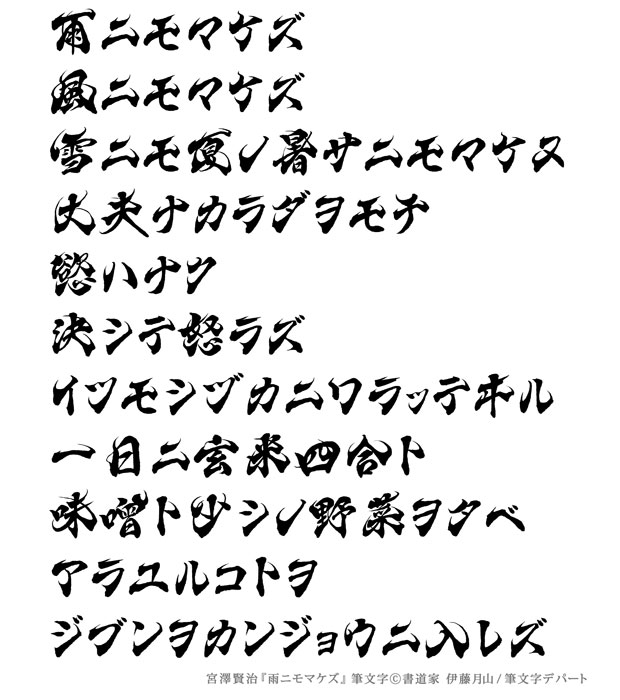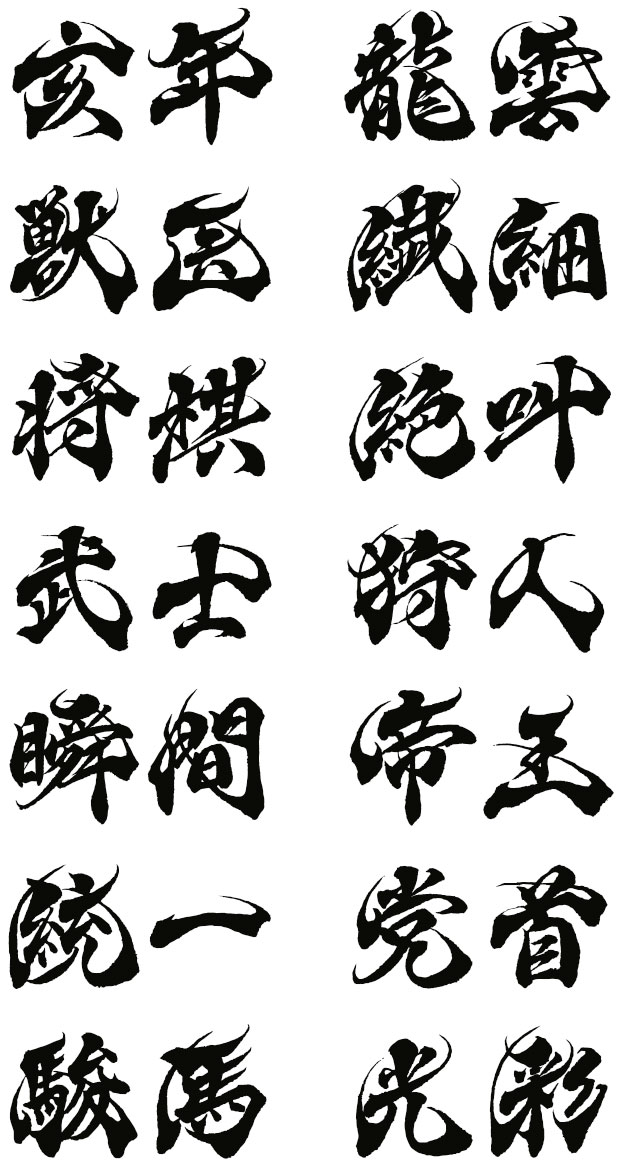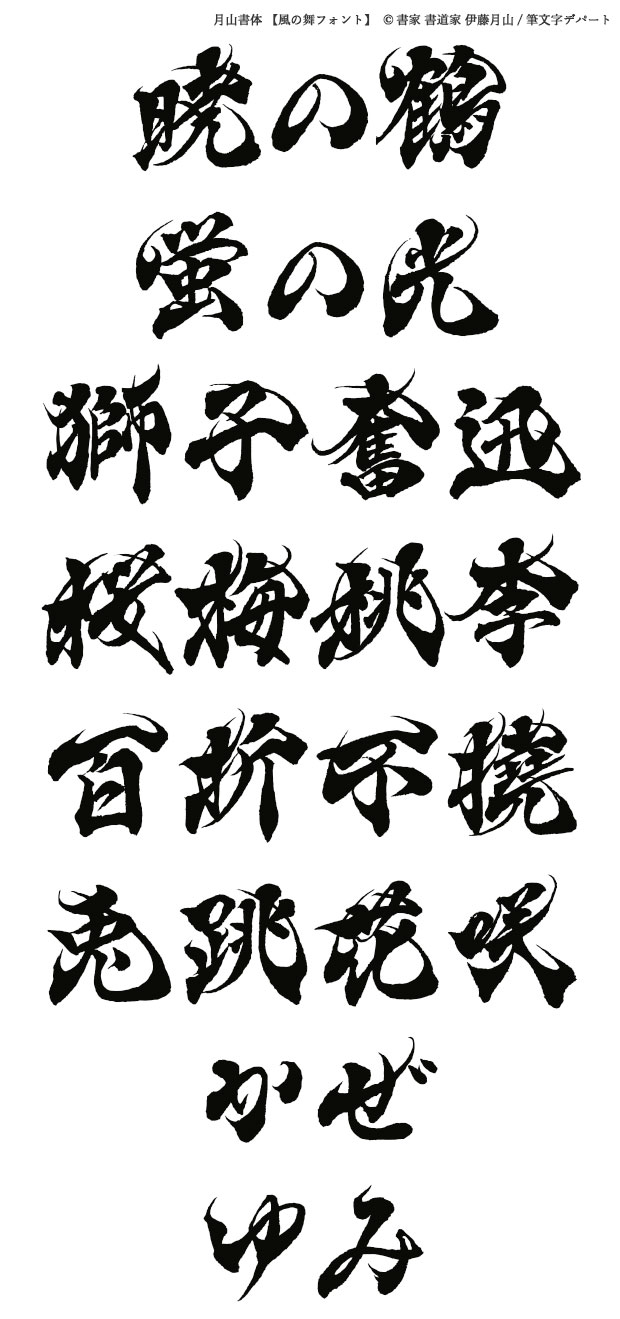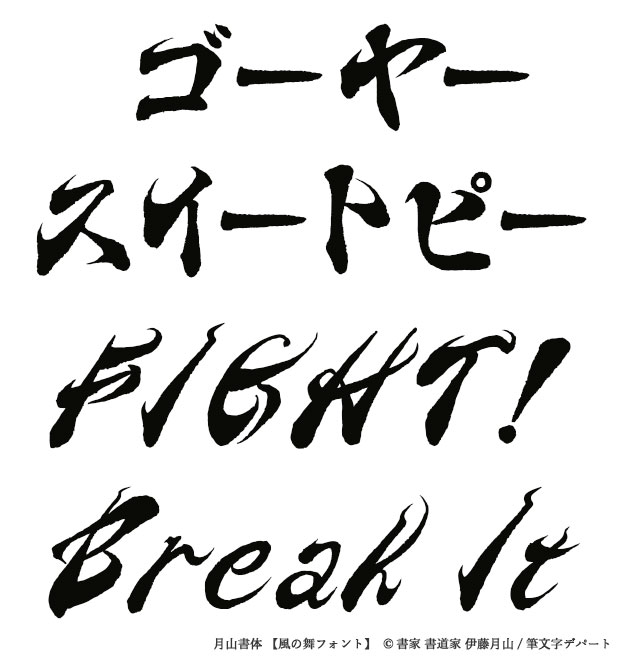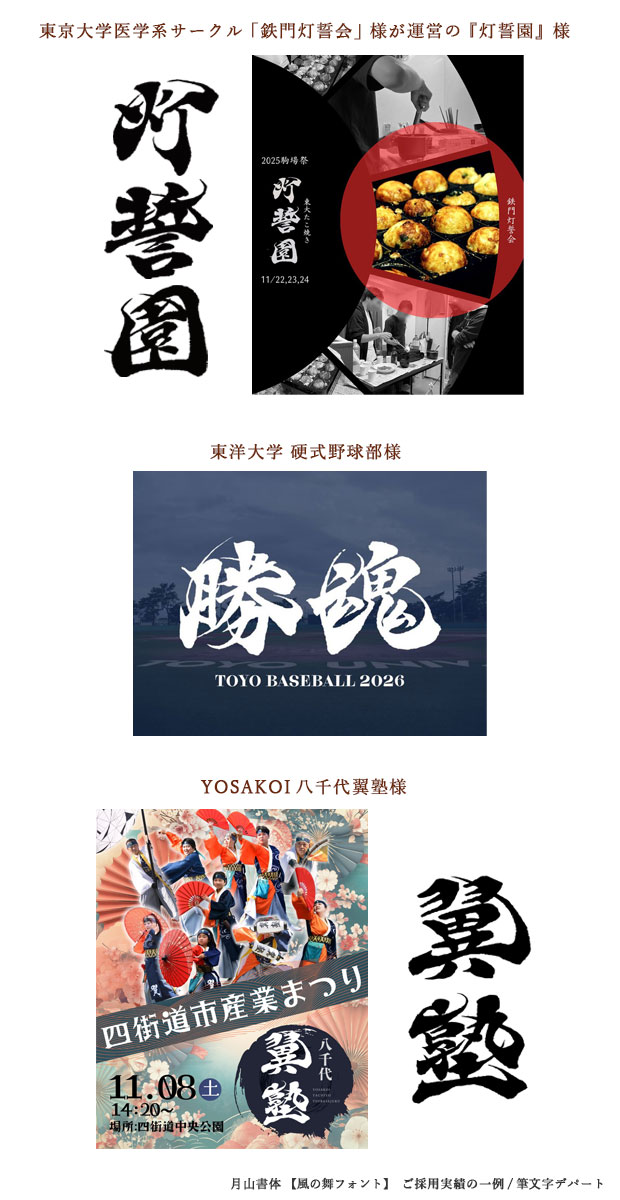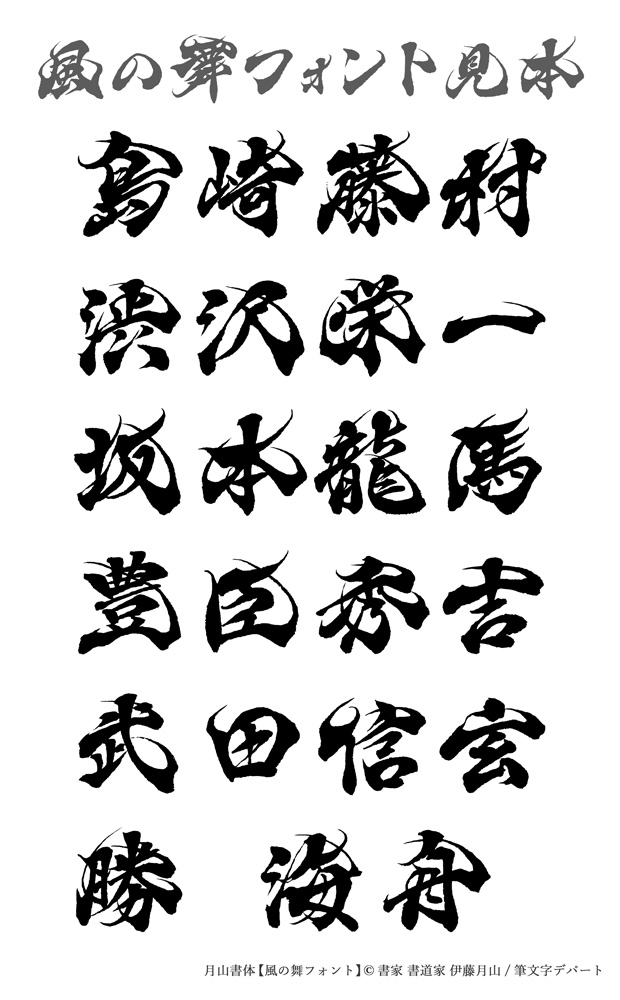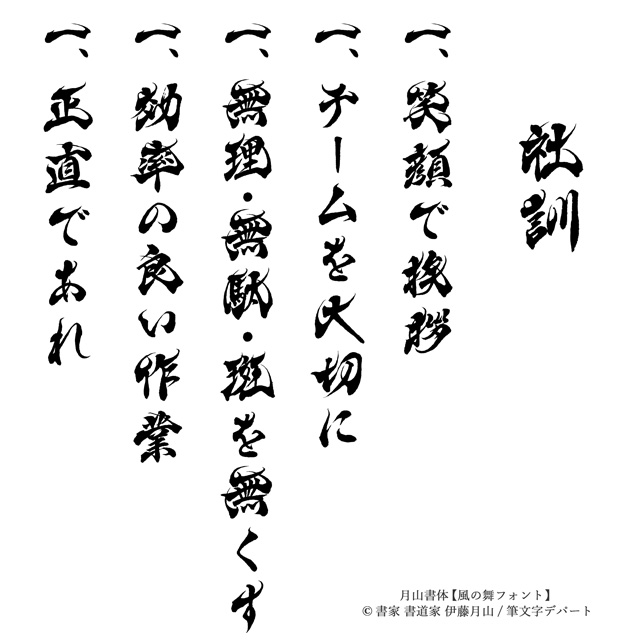
風の舞フォントA(一揃い)
個性的な毛筆デザインが特徴の「風の舞フォント」は、これまで1文字単位(1文字/1,650円)のみの販売を行なっておりましたが、広告代理店様やWeb制作会社様をはじめとする様々な業種の皆様より『一揃いの風の舞フォントとして使用したい』というご要望を多くいただき、約5年の制作期間を経てようやく販売を開始いたしました。
この風の舞フォントAは、常用漢字・JIS第一水準漢字・ひらがな・カタカナ・アルファベット・算用数字の全てを収録した一揃いのフォントです。
このフォントは1文字1文字が単独でも使える完成度を目指し、また可読性にも配慮し多数の実績を持つ書家/書道家 伊藤月山が心を込めて創作した自信作です。
動画、パッケージデザイン、デジタル広告、イベントの看板、新商品のラベル、番組タイトル、横断幕、のぼり旗、パンフレット、映像制作、名刺…など、商用利用・個人利用どちらにおいても複数の媒体に繰り返しご使用いただけます。様々なシーンで是非ご活用ください。
また、このフォントの書体は書家/書道家 伊藤月山(白水)が独自に考案した構成法「風舞書®」を応用した、完全オリジナルの個性的な毛筆書体です。そして漢字の偏(へん)や旁(つくり)の使い回しは一切せず、1文字ずつ手書きで丁寧に書き上げており、アンカーポイントを多く設けることで墨の滲みを具象化し書道の息吹を感じるよう仕上げております。
筆文字:【灯誓園】
東京大学医学系サークル『鉄門灯誓会』様が運営の本格たこ焼きの屋台『灯誓園』様。駒場祭にて看板・のぼり旗等にご使用いただきました。
筆文字:【勝魂】
東洋大学 硬式野球部様の2026年度のチームスローガンにご採用いただきました。
筆文字:【翼塾】
YOSAKOI八千代翼塾様のよさこいチームロゴにご活用いただいております。
風の舞フォントはその他、県知事の書籍、劇団のグッズ、高校のクラブ旗、だんじり祭りの小道具、熊野古道同好会Tシャツ、社訓、鮨店、バスケットボールの応援旗、同人誌タイトルロゴなど企業様、個人様問わず多種多様の用途で幅広くご注文をいただいております。
Q.風の舞フォントとは、どのようなフォントですか?
A.書家/書道家 伊藤月山が独自に考案した「風舞書®」をベースにつくられた、完全オリジナルの個性的な高級毛筆書体です。
「風に舞っている」ような、伸びやかで力強い動きのある毛筆デザインが特徴で、アンカーポイントを多く取ることで、紙に書いた時のような「墨のにじみ」が具象化されています。本物の書家による、書道の息吹を感じる当フォントを自信を持ってお薦めいたします。